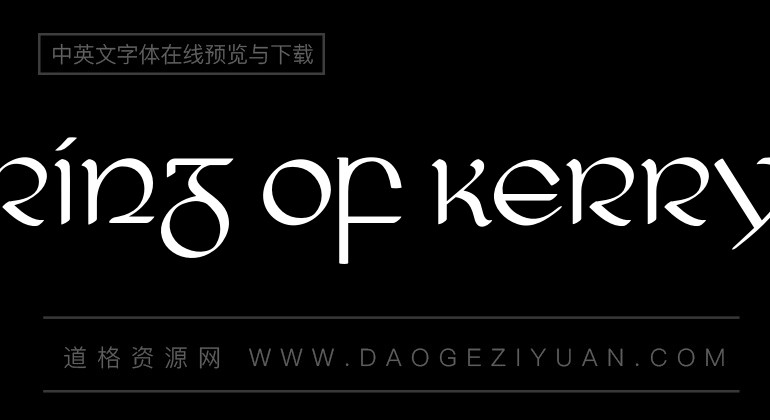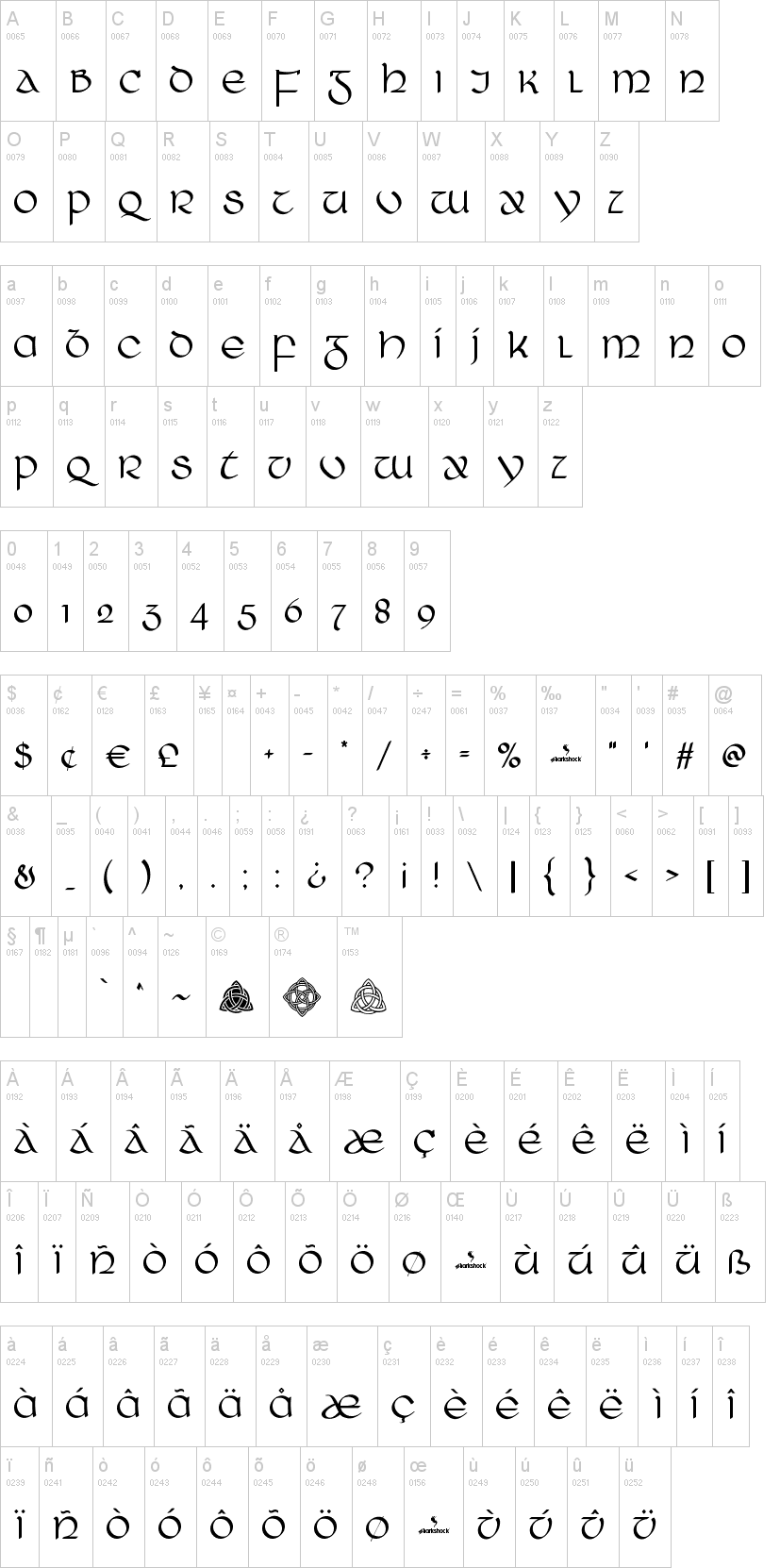
Ring of Kerry是爱尔兰最著名的旅游路线之一,它绕着爱尔兰的科尔郡(Kerry)环绕,从科克(Killarney)出发,经过南部的美丽海岸线,蜿蜒穿过群山,直到达到科克(Killarney)。Ring of Kerry的字体是一种英文古典楷体,其字形拥有清晰的笔画,比例协调,结构紧凑,给人以平静安宁的感觉。它是一种极具特色的字体,能够恰到好处地表达出Ring of Kerry的美丽风光。内容介绍
Ring of Kerry是一款非常不错的手写艺术字体,具有很好的视觉感,适合于文化类的宣传设计、商业类品牌的广告和产品包装设计以及个性化文字排版等较多场景。